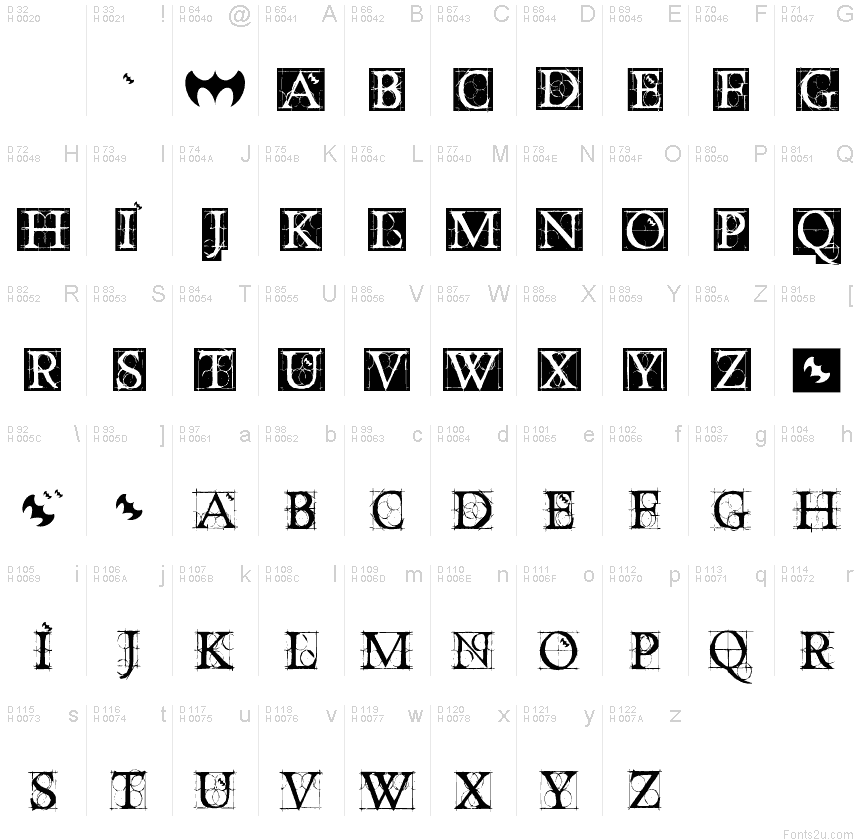
Dancing Vampyrish autorstwa M. Klein to darmowy, dekoracyjny krój pisma, który emanuje urokiem klasycznego horroru. Każda litera osadzona jest w surowej, poszarpanej ramce – niczym zakurzona etykieta wyrwana ze starego, gotyckiego manuskryptu – a kanciaste formy są jednocześnie teatralne i złowieszcze. Tekstura jest ziarnista i nierówna, co nadaje nagłówkom ręcznie wykonany, upiorny charakter, wyglądając niczym odbitka z sadzy lub wyschniętego atramentu.
Dzięki Dancing Vampyrish w kilka sekund stworzysz klimatyczne plakaty na Halloween, okładki książek grozy, szyldy do nawiedzonych domów, upiorne zaproszenia na imprezy czy mroczne tytuły gier. Ten darmowy font najlepiej sprawdza się w dużych rozmiarach, gdzie jego detale naprawdę przyciągają wzrok. W przypadku tekstu głównego zestaw go z prostym, wąskim krojem bezszeryfowym, aby zachować czytelność projektu, pozwalając jednocześnie, by nagłówki w stylu Vampyrish skradły całą uwagę.